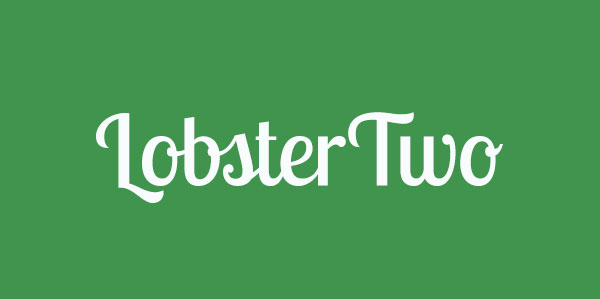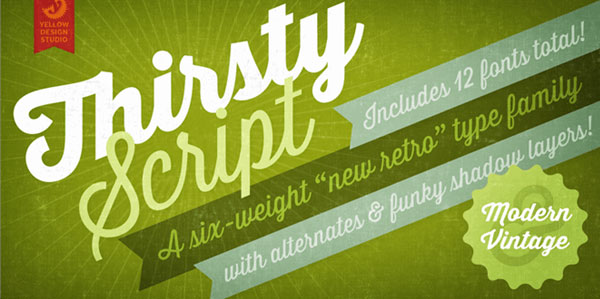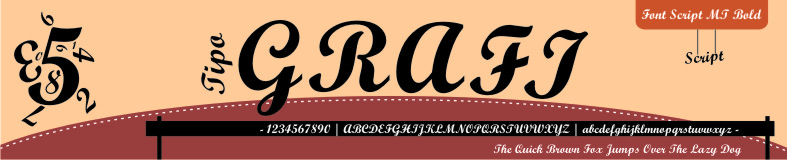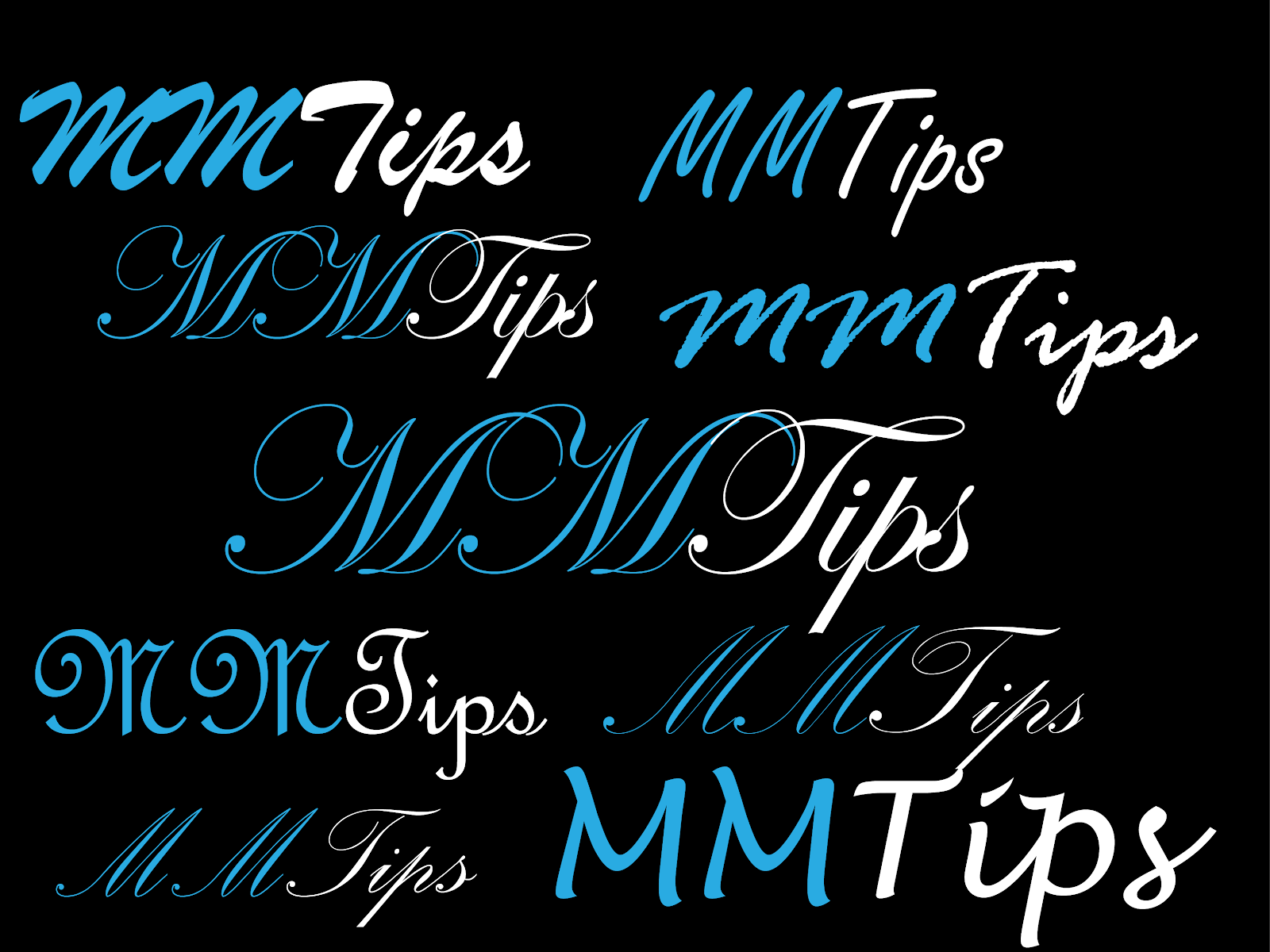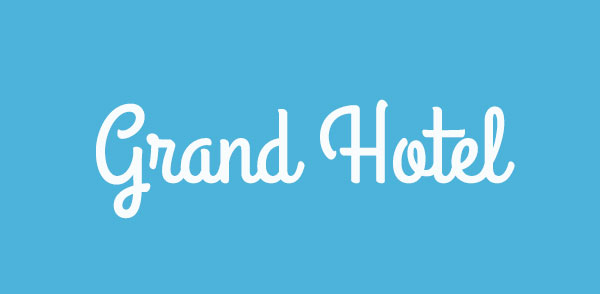
Fonts SVG PNG EPS DXF JPG AI Vector Qoutes File Script Jenis Font SVG. Browse by alphabetical listing, by style, by author or by popularity. Script typefaces are based upon the varied and often fluid stroke created by handwriting, pretty much like the cursive fonts just typically more elegant. They are organized into highly regular formal types. Font merupakan sebuah bentuk huruf yang mempunya ukuran, gaya, dan berat tertentu. Archive of freely downloadable fonts. Font script atau handwriting adalah jenis font yang lebih nampak natural dan elegan. Dalam dunia desain, jenis font dapat mempengaruhi desain yang akan ditampilkan. Salah satu ciri yang mencolok dari font script atau handwriting ini adalah seperti tulisan tangan dan kaligrafi. Font bisa kita temui di dimanapun terutama. Pernahkah kamu melihat tipografi yang mirip dengan tulisan tangan? Jenis font ini memiliki ciri yang khas seperti tulisan manusia pada umumnya, seperti tulisan dari kapur. Font monospace adalah jenis font yang lebar setiap karakternya sama panjang seperti courier, courier new, dan andale mono. Jenis font script adalah font yang lebih mengutamakan kesan perasaan kepada pembacanya. Jenis huruf ini mencangkup semua. Karena sifatnya itulah, font ini umumnya digunakan untuk menulis.
500 Gambar Script Font Terbaik Di 2020 Font Tipografi Font Gratis Monogram Logo. Jenis huruf ini mencangkup semua. They are organized into highly regular formal types. Jenis font script adalah font yang lebih mengutamakan kesan perasaan kepada pembacanya. Karena sifatnya itulah, font ini umumnya digunakan untuk menulis. Dalam dunia desain, jenis font dapat mempengaruhi desain yang akan ditampilkan. Font bisa kita temui di dimanapun terutama. Browse by alphabetical listing, by style, by author or by popularity. Archive of freely downloadable fonts. Font script atau handwriting adalah jenis font yang lebih nampak natural dan elegan. Pernahkah kamu melihat tipografi yang mirip dengan tulisan tangan? Script typefaces are based upon the varied and often fluid stroke created by handwriting, pretty much like the cursive fonts just typically more elegant. Font monospace adalah jenis font yang lebar setiap karakternya sama panjang seperti courier, courier new, dan andale mono. Salah satu ciri yang mencolok dari font script atau handwriting ini adalah seperti tulisan tangan dan kaligrafi. Font merupakan sebuah bentuk huruf yang mempunya ukuran, gaya, dan berat tertentu. Jenis font ini memiliki ciri yang khas seperti tulisan manusia pada umumnya, seperti tulisan dari kapur.
Jenis font ini memiliki ciri yang khas seperti tulisan manusia pada umumnya, seperti tulisan dari kapur. July 20, 2020july 20, 20201970's fonts cool fonts custom fonts free hipster fonts lettering fonts stencil fonts vintage fonts by hipfonts. Jenis font dekoratif punya ciri. Emanuele abrate adalah seorang perancang grafis asal italia. Beberapa contoh font script adalah segoe script, palace script mt, kaufmann bt. Jenis font script adalah font yang lebih mengutamakan kesan perasaan kepada pembacanya. The jeni font contains 86 beautifully designed characters. Collection by dewi meilani khairunnisa. Gunakan script jenis huruf png gratis ini untuk desain web, desain dtp, selebaran, proposal, proyek sekolah, poster, dan lainnya. Font script atau handwriting adalah jenis font yang lebih nampak natural dan elegan. Pernahkah kamu melihat tipografi yang mirip dengan tulisan tangan? Browse by alphabetical listing, by style, by author or by popularity. The best selection of script fonts for windows and macintosh. Script typefaces are based upon the varied and often fluid stroke created by handwriting, pretty much like the cursive fonts just typically more elegant. Font bisa kita temui di dimanapun terutama. Salah satu ciri yang mencolok dari font script atau handwriting ini adalah seperti tulisan tangan dan kaligrafi. Some scripts are more formal like elegant calligraphy, while others are casual like cursive handwriting. Yap, bisa jadi itu masuk ke dalam kategori jenis script font. Walaupun susah dicari, font ini banyak kegunaannya dan sangat langka. Dalam dunia desain, jenis font dapat mempengaruhi desain yang akan ditampilkan. Hubungi pengunggah untuk mendapatkan lebih banyak manfaat seperti. Karena sifatnya itulah, font ini umumnya digunakan untuk menulis. Jenis font script itu font yang lebih mengutamakan kesan perasaan kepada pembacanya. Contoh dari font jenis ini adalah arial, verdana, trebuchet ms, helvetica, dan calibri. Jenis font ini juga biasa disebut font display atau font ornamental. Archive of freely downloadable fonts. Jenis font ini memiliki ciri yang khas seperti tulisan manusia pada umumnya, seperti tulisan dari kapur. Download and install free script fonts of the best quality from free fonts and use on your own personal and business related design purposes. Download 10,000 fonts with one click for $19.95. Font merupakan sebuah bentuk huruf yang mempunya ukuran, gaya, dan berat tertentu. Sebuah logo dengan font jenis script akan memberi kesan berbeda dengan logo dengan font jenis sans serif.
Mengenal Jenis Jenis Font Eugenia Caroline. Dalam dunia desain, jenis font dapat mempengaruhi desain yang akan ditampilkan. Browse by alphabetical listing, by style, by author or by popularity. Salah satu ciri yang mencolok dari font script atau handwriting ini adalah seperti tulisan tangan dan kaligrafi. Pernahkah kamu melihat tipografi yang mirip dengan tulisan tangan? Archive of freely downloadable fonts. Font bisa kita temui di dimanapun terutama. They are organized into highly regular formal types. Font monospace adalah jenis font yang lebar setiap karakternya sama panjang seperti courier, courier new, dan andale mono. Jenis font script adalah font yang lebih mengutamakan kesan perasaan kepada pembacanya. Jenis font ini memiliki ciri yang khas seperti tulisan manusia pada umumnya, seperti tulisan dari kapur. Font script atau handwriting adalah jenis font yang lebih nampak natural dan elegan. Script typefaces are based upon the varied and often fluid stroke created by handwriting, pretty much like the cursive fonts just typically more elegant. Jenis huruf ini mencangkup semua. Font merupakan sebuah bentuk huruf yang mempunya ukuran, gaya, dan berat tertentu. Karena sifatnya itulah, font ini umumnya digunakan untuk menulis.
Emanuele abrate adalah seorang perancang grafis asal italia.
Kenali Jenis Font Dalam Desain Grafis Saveas Brand Blog Artikel Desain Grafis Dan Komunikasi. They are organized into highly regular formal types. Browse by alphabetical listing, by style, by author or by popularity. Jenis huruf ini mencangkup semua. Salah satu ciri yang mencolok dari font script atau handwriting ini adalah seperti tulisan tangan dan kaligrafi. Font merupakan sebuah bentuk huruf yang mempunya ukuran, gaya, dan berat tertentu. Jenis font script adalah font yang lebih mengutamakan kesan perasaan kepada pembacanya. Script typefaces are based upon the varied and often fluid stroke created by handwriting, pretty much like the cursive fonts just typically more elegant. Dalam dunia desain, jenis font dapat mempengaruhi desain yang akan ditampilkan. Pernahkah kamu melihat tipografi yang mirip dengan tulisan tangan? Karena sifatnya itulah, font ini umumnya digunakan untuk menulis. Font script atau handwriting adalah jenis font yang lebih nampak natural dan elegan. Font monospace adalah jenis font yang lebar setiap karakternya sama panjang seperti courier, courier new, dan andale mono. Archive of freely downloadable fonts. Jenis font ini memiliki ciri yang khas seperti tulisan manusia pada umumnya, seperti tulisan dari kapur. Font bisa kita temui di dimanapun terutama.
Karena sifatnya itulah, font ini umumnya digunakan untuk menulis.
500 Gambar Script Font Terbaik Di 2020 Font Tipografi Font Gratis Monogram Logo. Jenis font ini memiliki ciri yang khas seperti tulisan manusia pada umumnya, seperti tulisan dari kapur. Script typefaces are based upon the varied and often fluid stroke created by handwriting, pretty much like the cursive fonts just typically more elegant. Jenis font script adalah font yang lebih mengutamakan kesan perasaan kepada pembacanya. Jenis huruf ini mencangkup semua. Salah satu ciri yang mencolok dari font script atau handwriting ini adalah seperti tulisan tangan dan kaligrafi. They are organized into highly regular formal types. Font merupakan sebuah bentuk huruf yang mempunya ukuran, gaya, dan berat tertentu. Font script atau handwriting adalah jenis font yang lebih nampak natural dan elegan. Dalam dunia desain, jenis font dapat mempengaruhi desain yang akan ditampilkan. Archive of freely downloadable fonts. Browse by alphabetical listing, by style, by author or by popularity. Karena sifatnya itulah, font ini umumnya digunakan untuk menulis. Font bisa kita temui di dimanapun terutama. Pernahkah kamu melihat tipografi yang mirip dengan tulisan tangan? Font monospace adalah jenis font yang lebar setiap karakternya sama panjang seperti courier, courier new, dan andale mono.
Jenis font script itu font yang lebih mengutamakan kesan perasaan kepada pembacanya.
Jenis Jenis Font Script Pict By Choidonghoon Wordpress Com Huruf Tulisan Literasi. Font merupakan sebuah bentuk huruf yang mempunya ukuran, gaya, dan berat tertentu. Jenis huruf ini mencangkup semua. Archive of freely downloadable fonts. Font script atau handwriting adalah jenis font yang lebih nampak natural dan elegan. Script typefaces are based upon the varied and often fluid stroke created by handwriting, pretty much like the cursive fonts just typically more elegant. Karena sifatnya itulah, font ini umumnya digunakan untuk menulis. Salah satu ciri yang mencolok dari font script atau handwriting ini adalah seperti tulisan tangan dan kaligrafi. Font monospace adalah jenis font yang lebar setiap karakternya sama panjang seperti courier, courier new, dan andale mono. Jenis font ini memiliki ciri yang khas seperti tulisan manusia pada umumnya, seperti tulisan dari kapur. Dalam dunia desain, jenis font dapat mempengaruhi desain yang akan ditampilkan. Browse by alphabetical listing, by style, by author or by popularity. Pernahkah kamu melihat tipografi yang mirip dengan tulisan tangan? Jenis font script adalah font yang lebih mengutamakan kesan perasaan kepada pembacanya. Font bisa kita temui di dimanapun terutama. They are organized into highly regular formal types.
Download 15 Font Script Handwritten Untuk Desain Tipografi Kumpulan Tutorial. Font merupakan sebuah bentuk huruf yang mempunya ukuran, gaya, dan berat tertentu. Karena sifatnya itulah, font ini umumnya digunakan untuk menulis. Dalam dunia desain, jenis font dapat mempengaruhi desain yang akan ditampilkan. Archive of freely downloadable fonts. Font monospace adalah jenis font yang lebar setiap karakternya sama panjang seperti courier, courier new, dan andale mono. Salah satu ciri yang mencolok dari font script atau handwriting ini adalah seperti tulisan tangan dan kaligrafi. Browse by alphabetical listing, by style, by author or by popularity. They are organized into highly regular formal types. Font script atau handwriting adalah jenis font yang lebih nampak natural dan elegan. Jenis huruf ini mencangkup semua. Jenis font script adalah font yang lebih mengutamakan kesan perasaan kepada pembacanya. Jenis font ini memiliki ciri yang khas seperti tulisan manusia pada umumnya, seperti tulisan dari kapur. Font bisa kita temui di dimanapun terutama. Pernahkah kamu melihat tipografi yang mirip dengan tulisan tangan? Script typefaces are based upon the varied and often fluid stroke created by handwriting, pretty much like the cursive fonts just typically more elegant.
Font script atau handwriting adalah jenis font yang lebih nampak natural dan elegan. Hubungi pengunggah untuk mendapatkan lebih banyak manfaat seperti. Gunakan script jenis huruf png gratis ini untuk desain web, desain dtp, selebaran, proposal, proyek sekolah, poster, dan lainnya. Salah satu ciri yang mencolok dari font script atau handwriting ini adalah seperti tulisan tangan dan kaligrafi. Contoh dari font jenis ini adalah arial, verdana, trebuchet ms, helvetica, dan calibri. This fonts copyright 1997 jeni pleskow. Jenis font script adalah font yang lebih mengutamakan kesan perasaan kepada pembacanya. Karena sifatnya itulah, font ini umumnya digunakan untuk menulis. The jeni font contains 86 beautifully designed characters. Jenis font ini juga biasa disebut font display atau font ornamental.